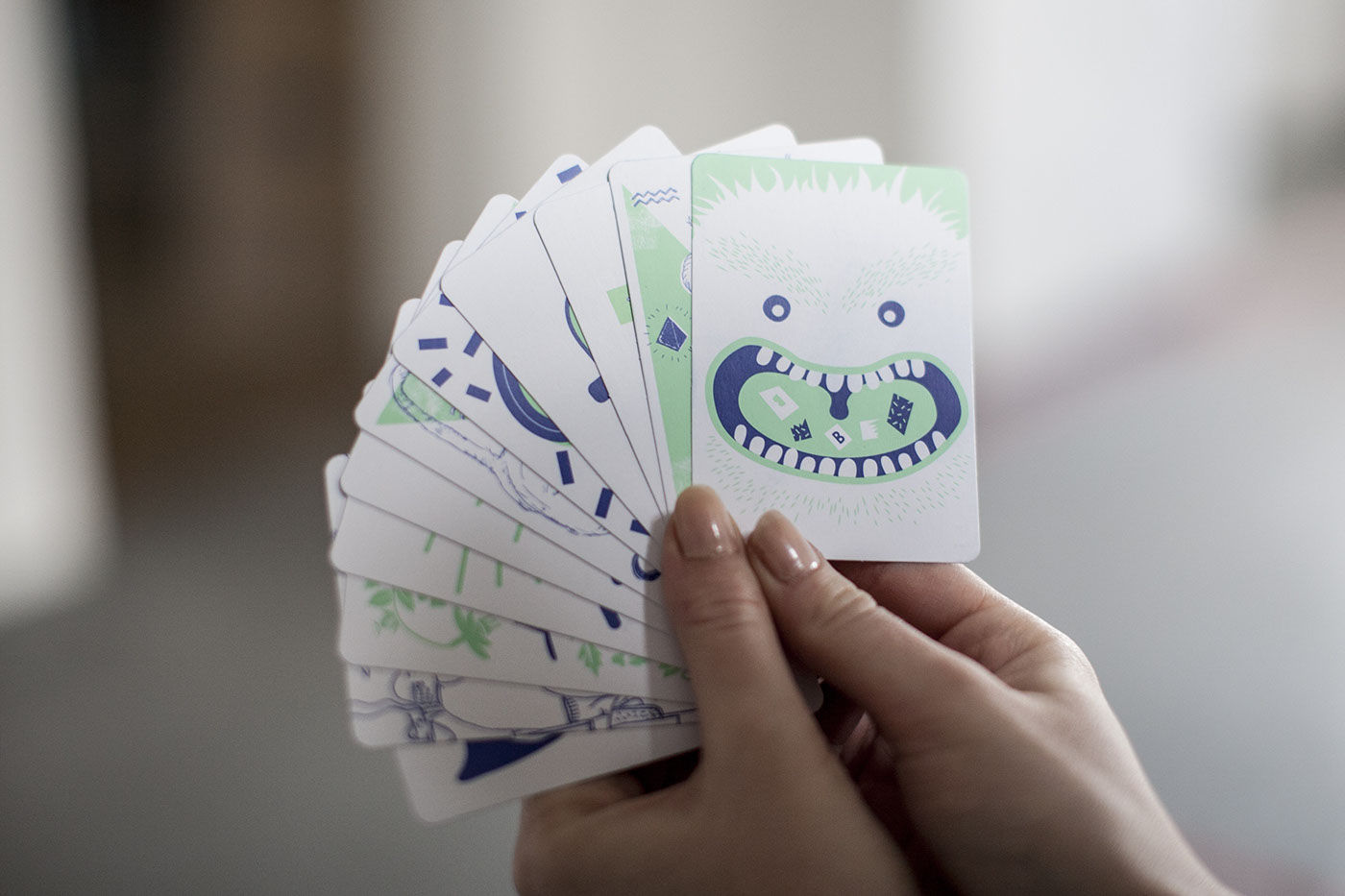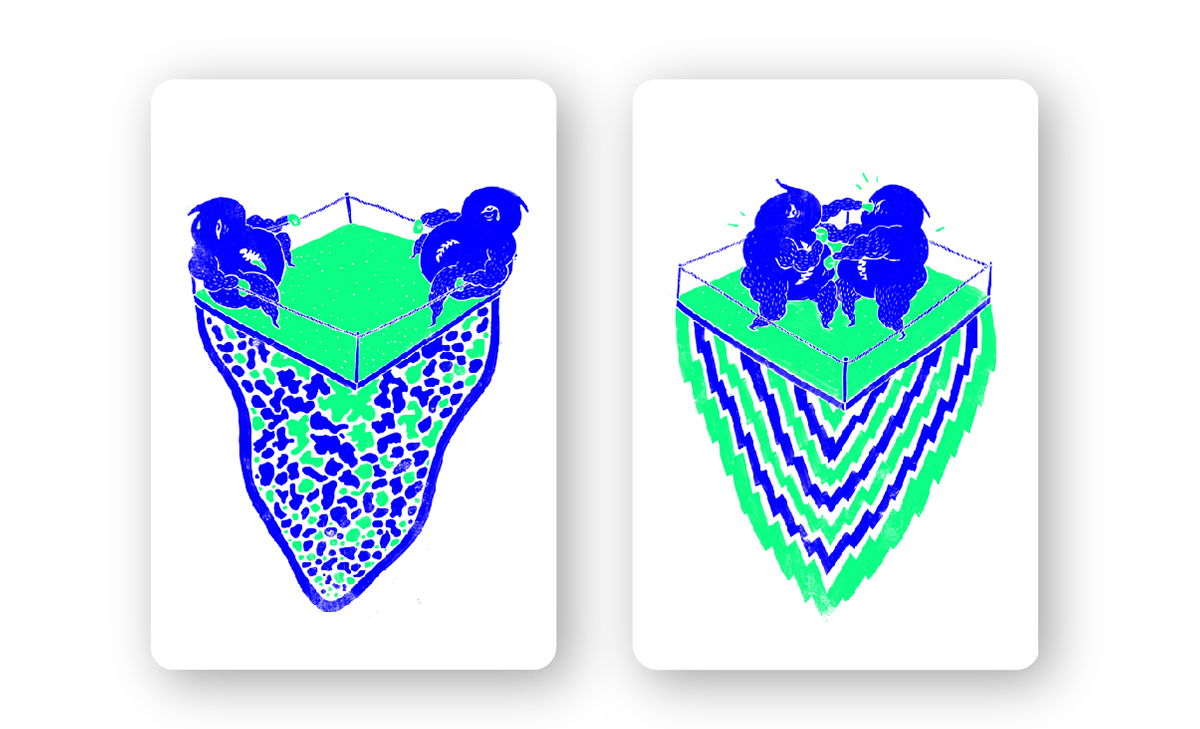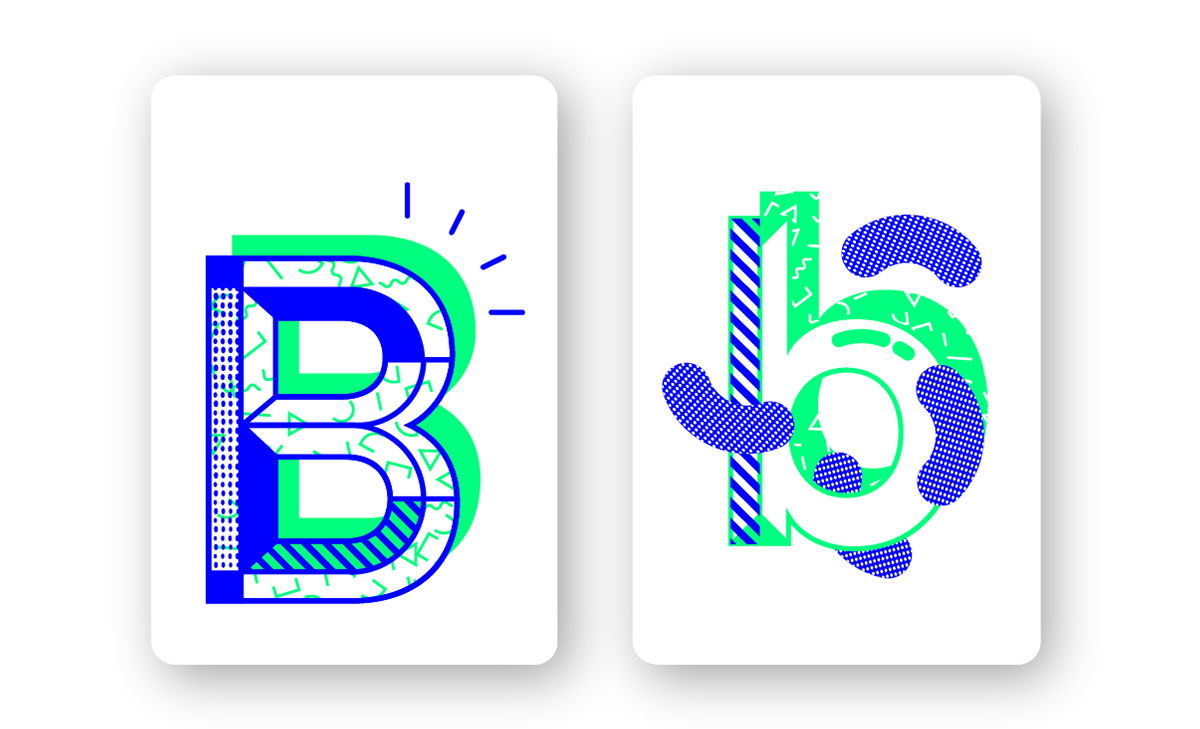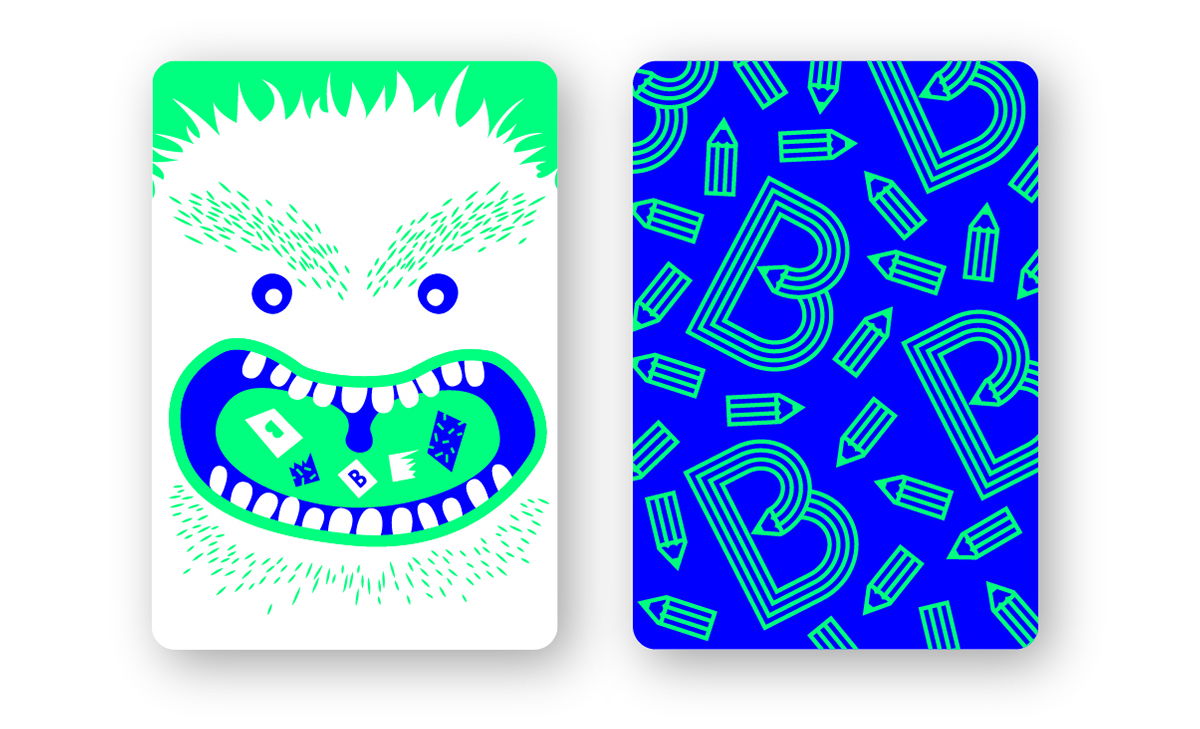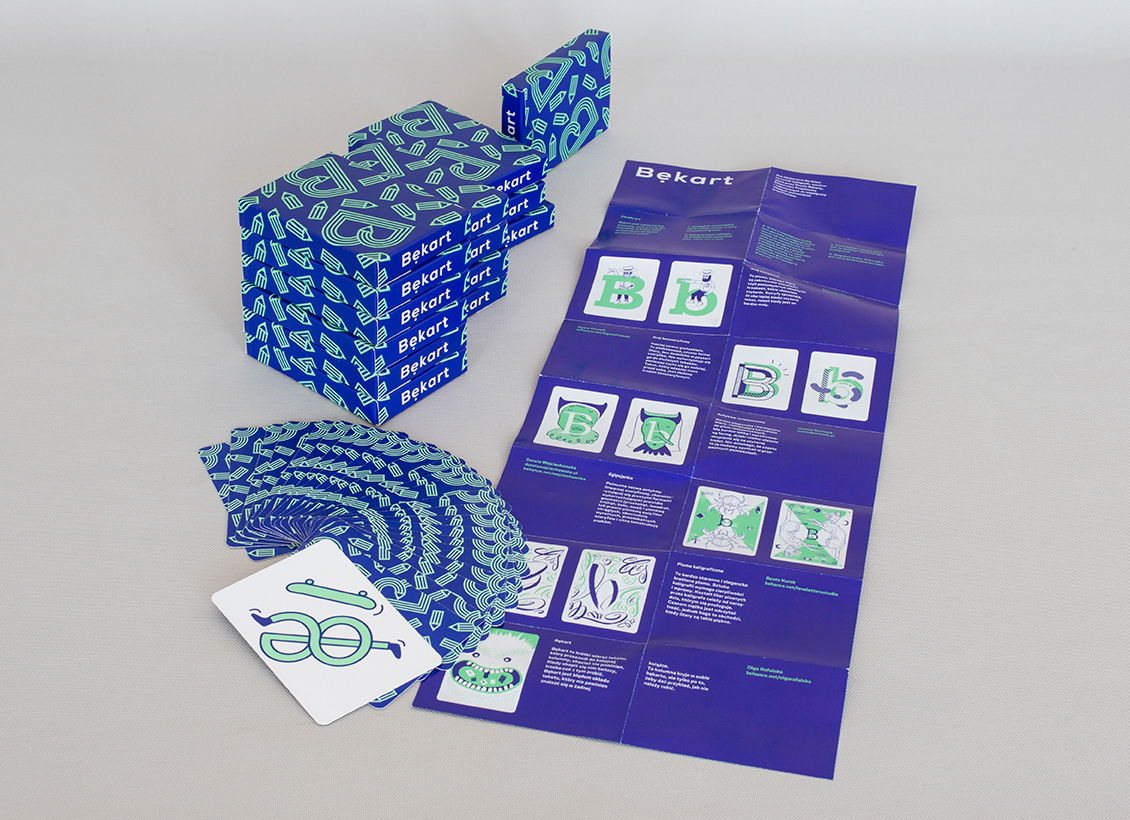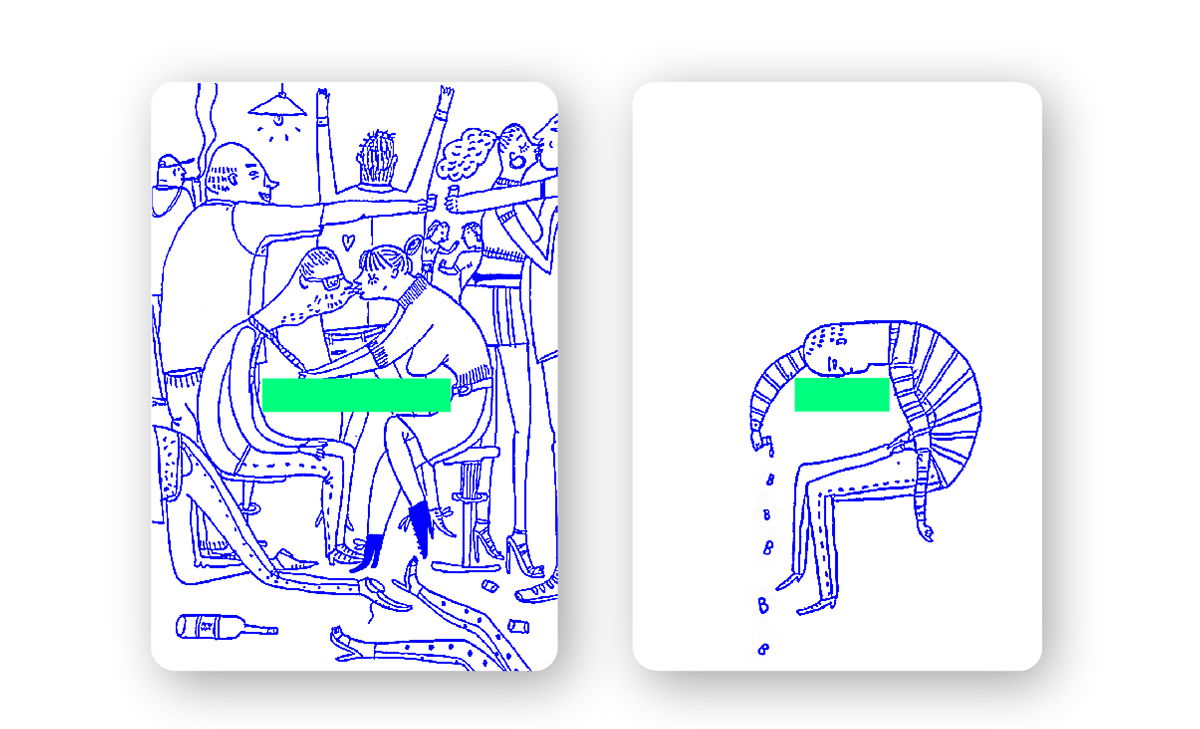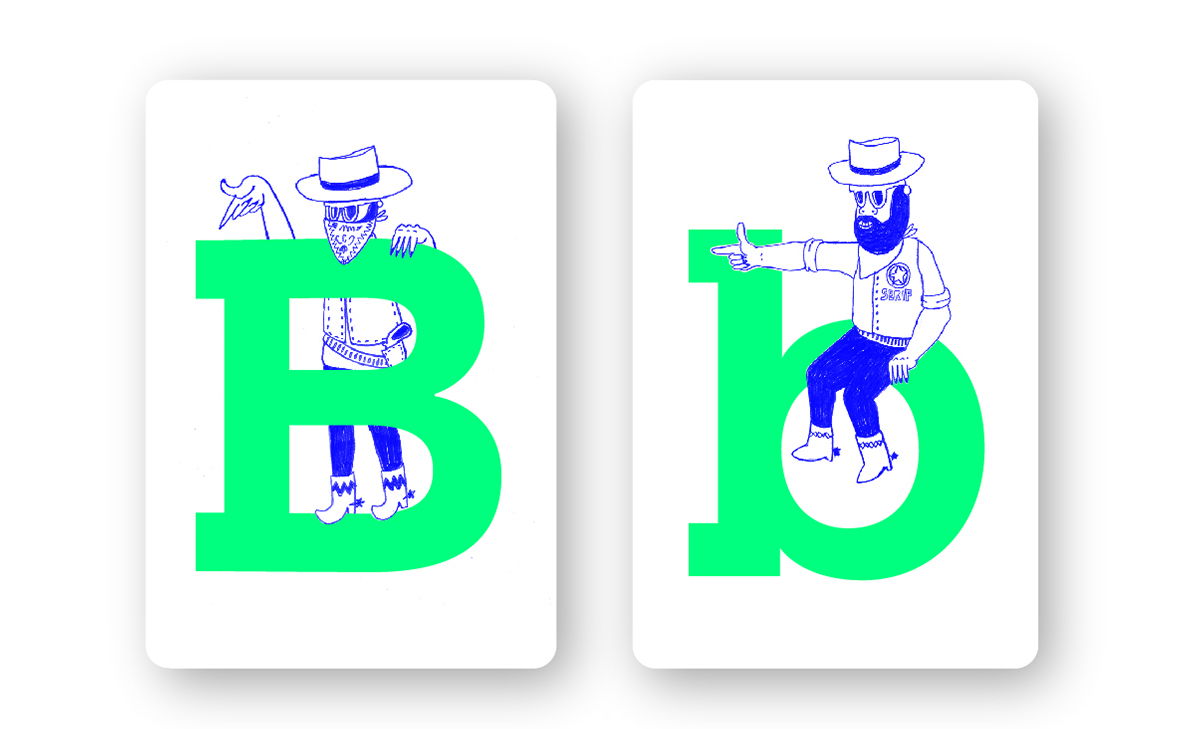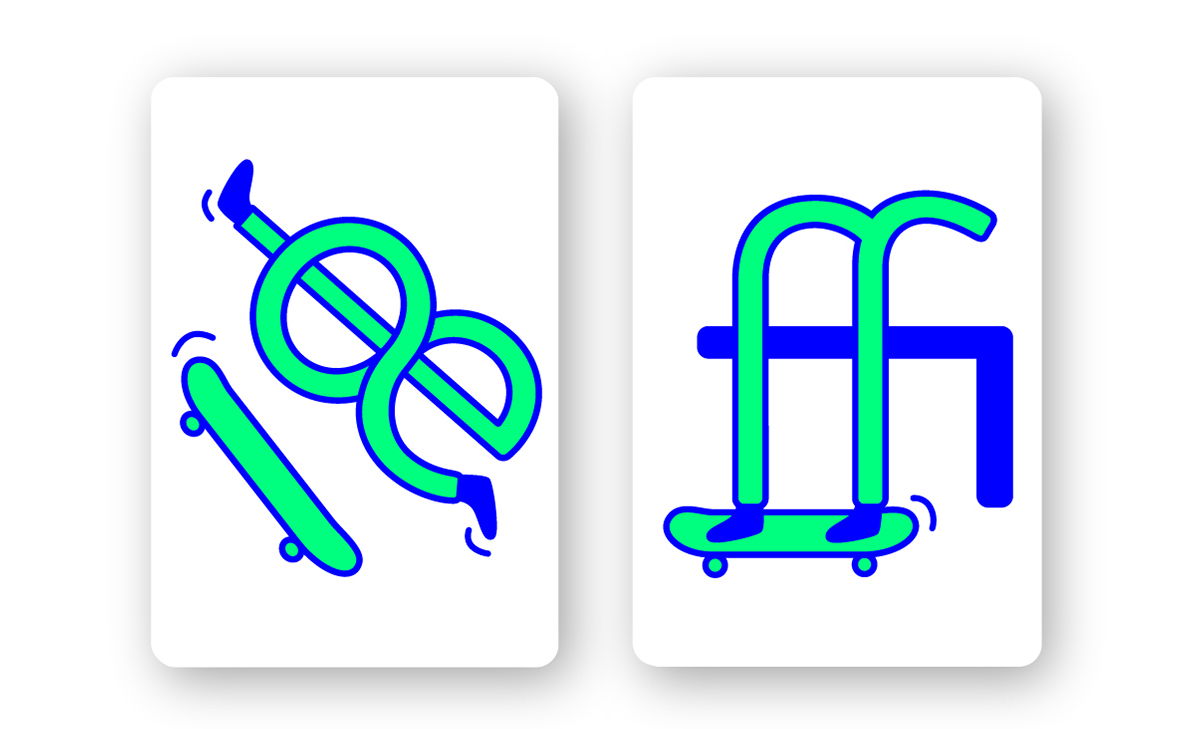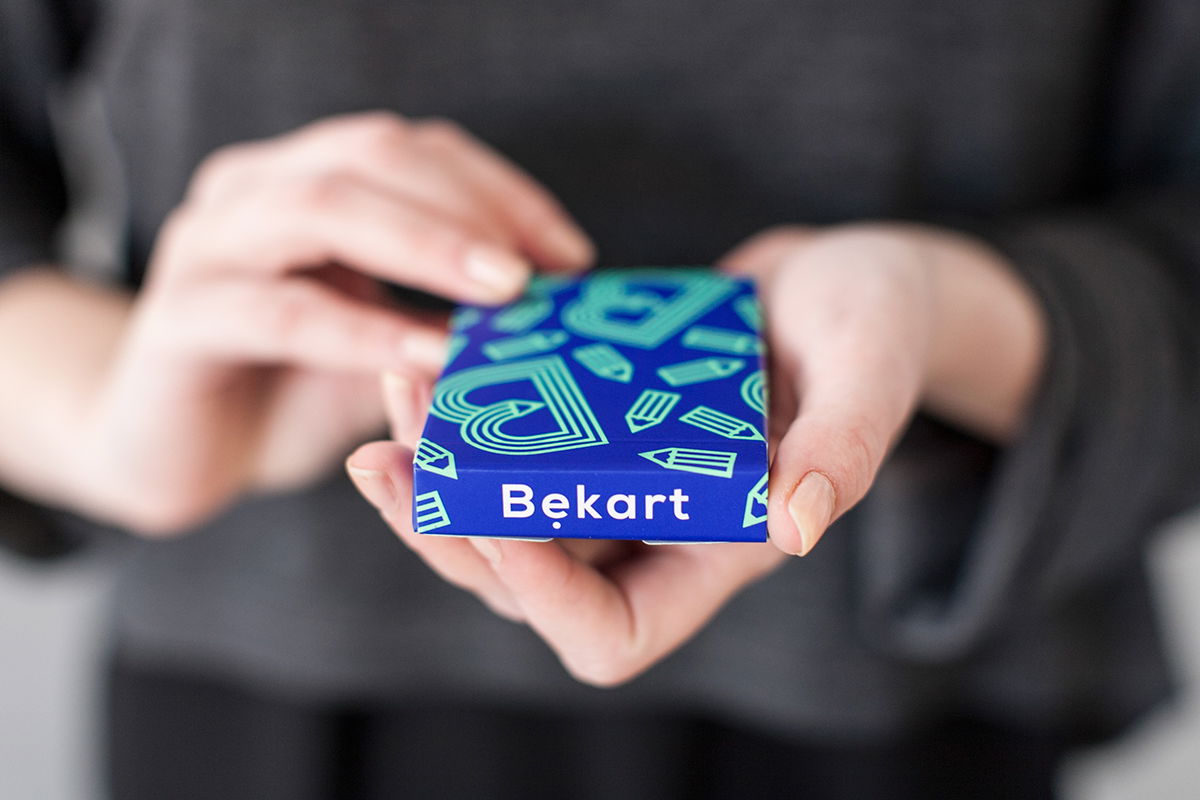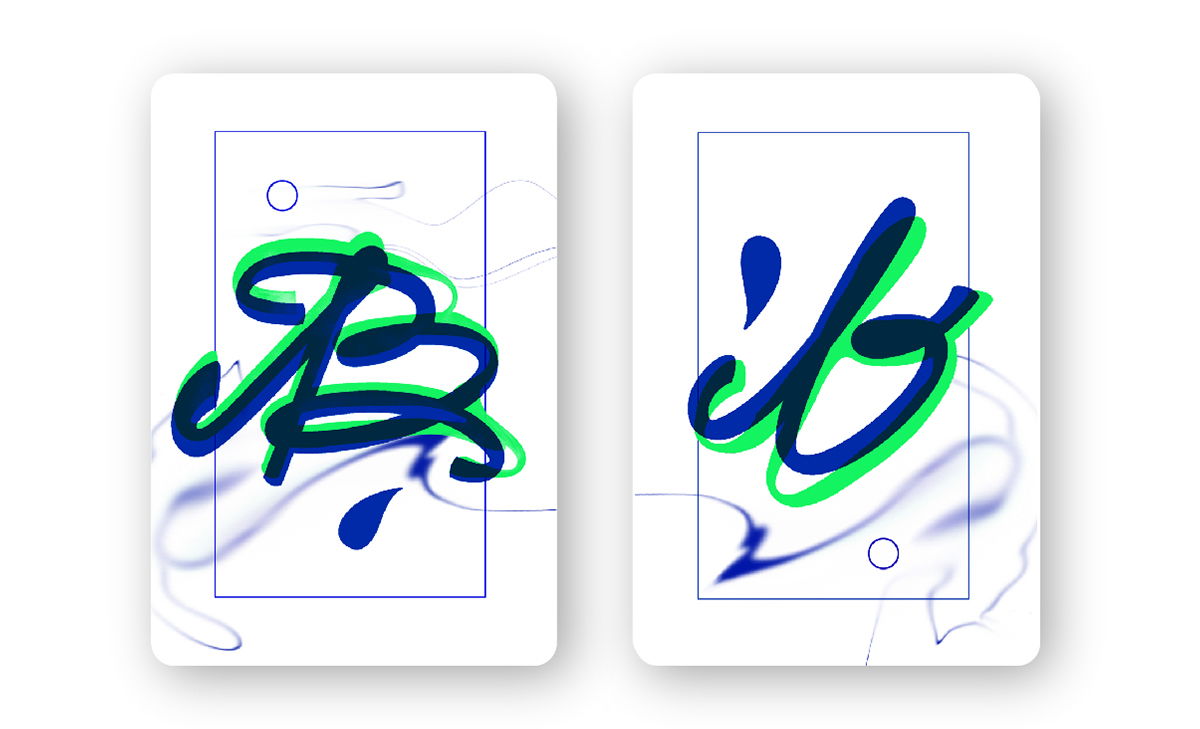
'Bękart', las cartas para aprender tipografía jugando
Los juegos de cartas siempre han sido un buen soporte para el arte. Si, además, un juego bien diseñado se hace con fines educativos, el resultado puede ser tan admirable por su estética como por su utilidad.
En Polonia, Elementarz Projectana y Bękarty Studio se han aliado para crear el regalo perfecto para los amantes de la tipografía. Aunque existen otros juegos de cartas en los que la tipografía adquiere gran importancia, pocos han logrado combinar el diseño y la didáctica como Bękart.
«La idea fue de Bękarty Studio. Ellos vinieron con el concepto del juego tipográfico. Nos encantó la idea, así que la desarrollamos juntos. Seleccionamos los temas de cada par e invitamos a jóvenes y talentosos diseñadores para que colaborasen con nosotros», cuenta Olga Rafalska, de Elementarz Projectana, a Yorokobu.
Varias diseñadoras de Poznan (Polonia) se unieron al proyecto: Miss Czuz, Zuzanna Rogatty, Dorota Wojciechowska, LoveLetters Studio, Iwona Przybyla, Agata Polasik, Marta Pitas Tomiak, Ja576 Ja576, Viktoriya Gravowska y Dominika Czerniak.
Dice Olga Rafalska que Bękart tiene dos objetivos: «El primero es ampliar el conocimiento de la gente sobre la tipografía y el segundo, promocionar a jóvenes y talentosos diseñadores polacos. Por eso quisimos presentar las nociones más básicas de la tipografía a través de ilustraciones juguetonas».
La primera vez que presentaron Bękart fue en la conferencia de diseño de Elementarz Projectana de este año y, según asegura Olga, fue un gran éxito. El juego, para la gente de letras como para la de números, es accesible a todos: «Aunque es un juego orientado a los niños, por su diseño también es muy popular entre diseñadores».
Olga Rafalska y Paulina Kakprzak fueron las responsables de la dirección creativa del reverso de las cartas y de los distintos diseños. Bekarty Studio, por su parte, se encargó de la información sobre tipografía que contiene el juego.
Bękart es una versión de ‘Black Peter’ (‘Old maid’) que sus autoras dieron a conocer en Behance. Contiene veintinco cartas, de las cuales veinticuatro están emparejadas y ‘bastard’, la carta ilustrada por un adorable monstruo, queda suelta.